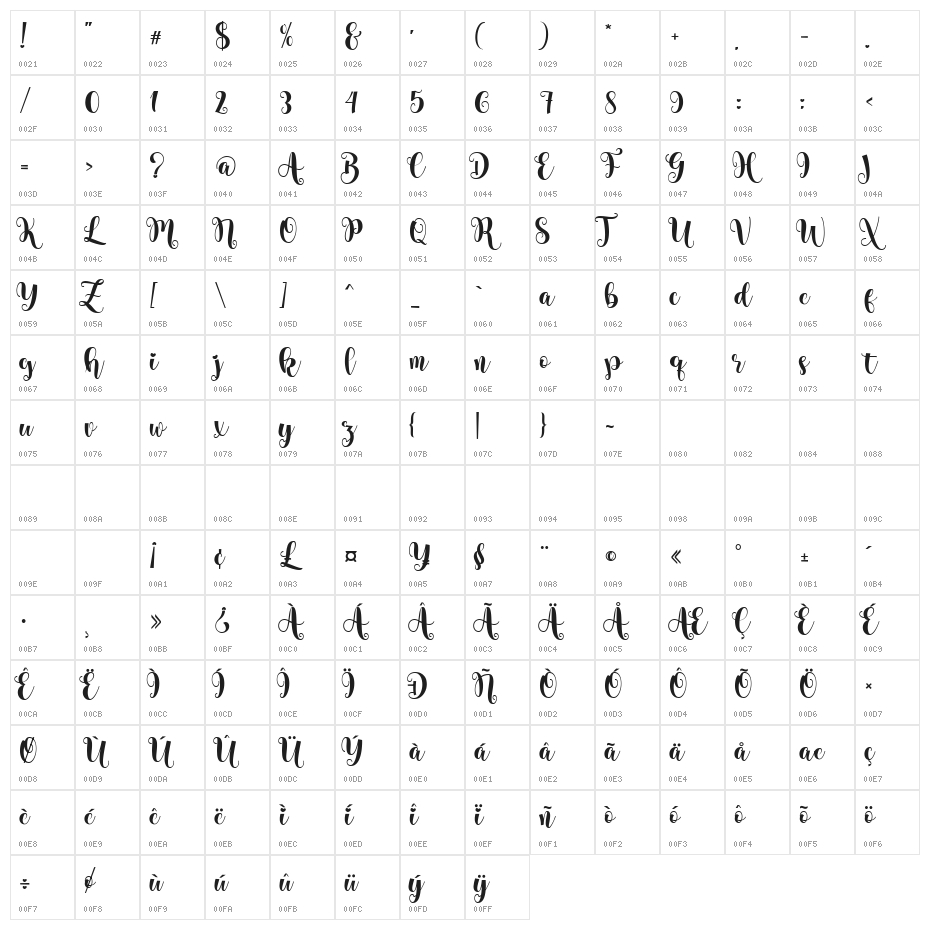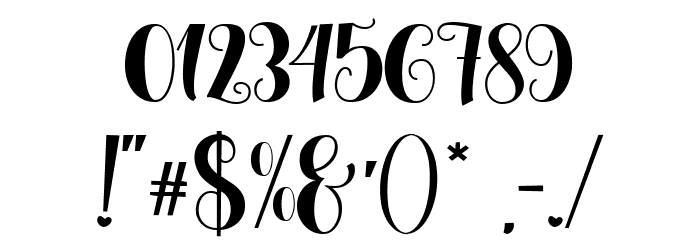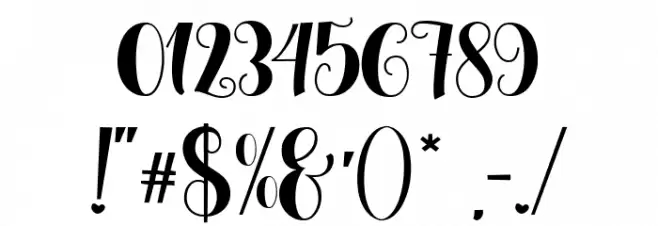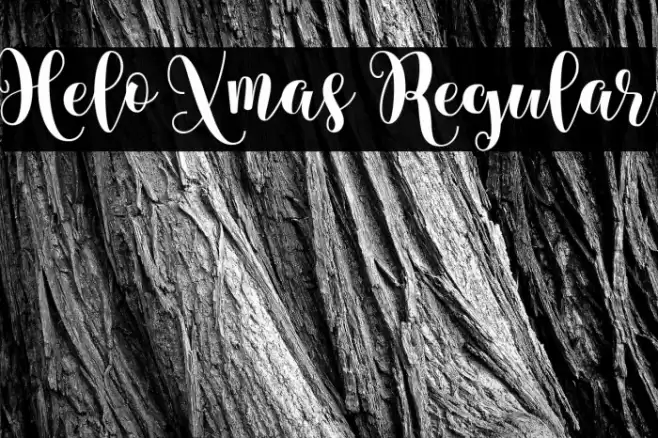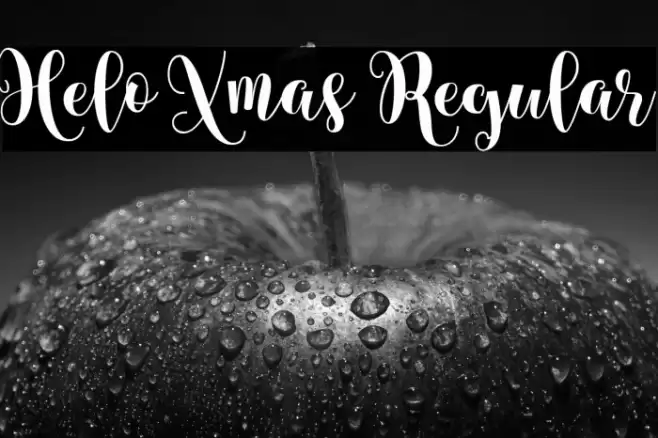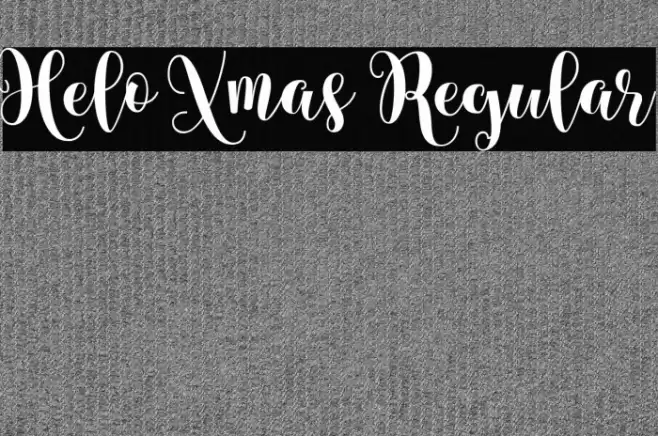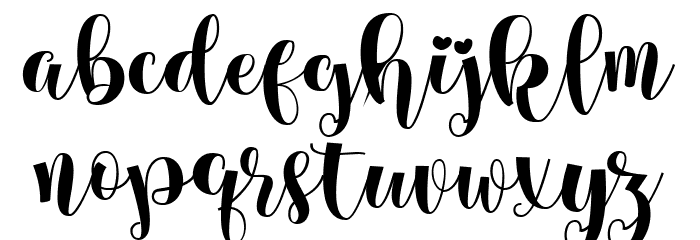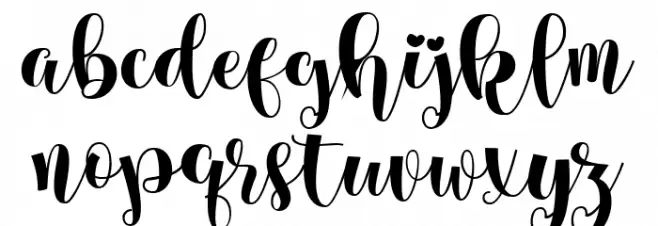
Helo Xmas Regular Font
| Schriften Familie | Helo Xmas |
| Anwendungsfall | Headlines, Logos, Invitations |
| Vorgeschlagene Projekte | Ideal for holiday cards, invitations, festive branding, and decorative signage. |